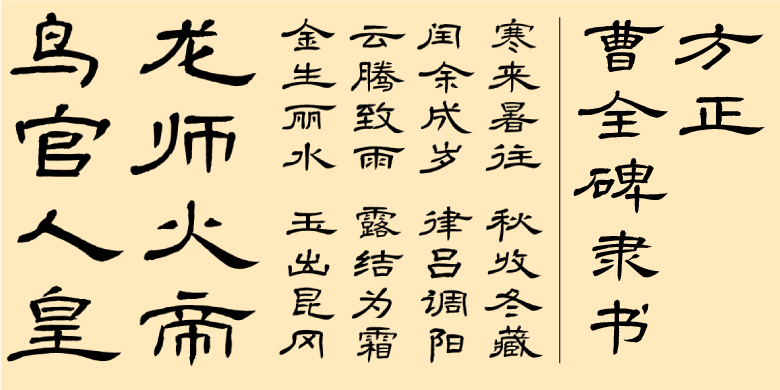
方正曹全碑隶书
方正曹全碑隶书,这款字体结构工整、笔画清晰,兼顾美观与易读性,适用于标题、正文、海报、包装、LOGO 等多种场景。字形优雅稳定,风格百搭耐看,适配日常排版与创意设计,让文字呈现更舒适、更具质感。方正曹全碑隶书一笔一画,皆是细节,以均衡的比例、流畅的线条打造舒适视觉体验,字形端正大气,风格简约现代。无论是商业设计、品牌宣传还是日常排版,都能轻松驾驭,让文字更有格调与力量。方正曹全碑隶书字体下载。
关于曹全碑:
《曹全碑》全称《汉郃阳令曹全碑》,东汉中平二年,由王敞等人镌立,该碑字数较多,是汉代隶书的代表作品之一,现存于陕西西安博物馆碑林。曹全碑碑文以风格秀逸多姿和结体匀整著称于世,历来为书家所重。
字体特征:
字迹娟秀清丽,结体扁平匀称,笔画舒展超逸,风致翩翩,有“回眸一笑百媚生”之态。
临创者:符世明
整理/设计:杨龙龙、张全、刘婷婷、张培艳、韩文静、刘晶、刘昱程、陈羽、史通通、曹基殿